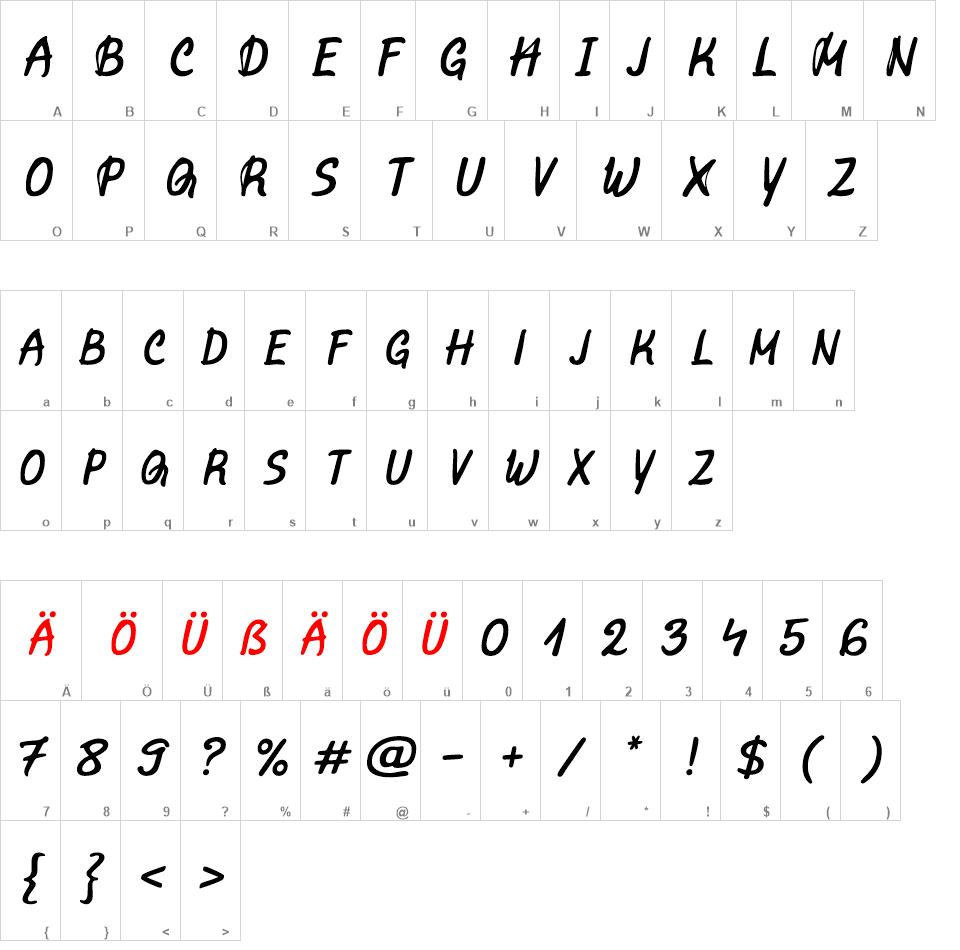
Marvelous Rex
Marvelous Rex font
Marvelous Rex
Marvellous Rex ist eine handgezeichnete Schrift, die vom Comic-Buch-Schriftzug inspiriert ist und auf vielfältige Weise verwendet werden kann.